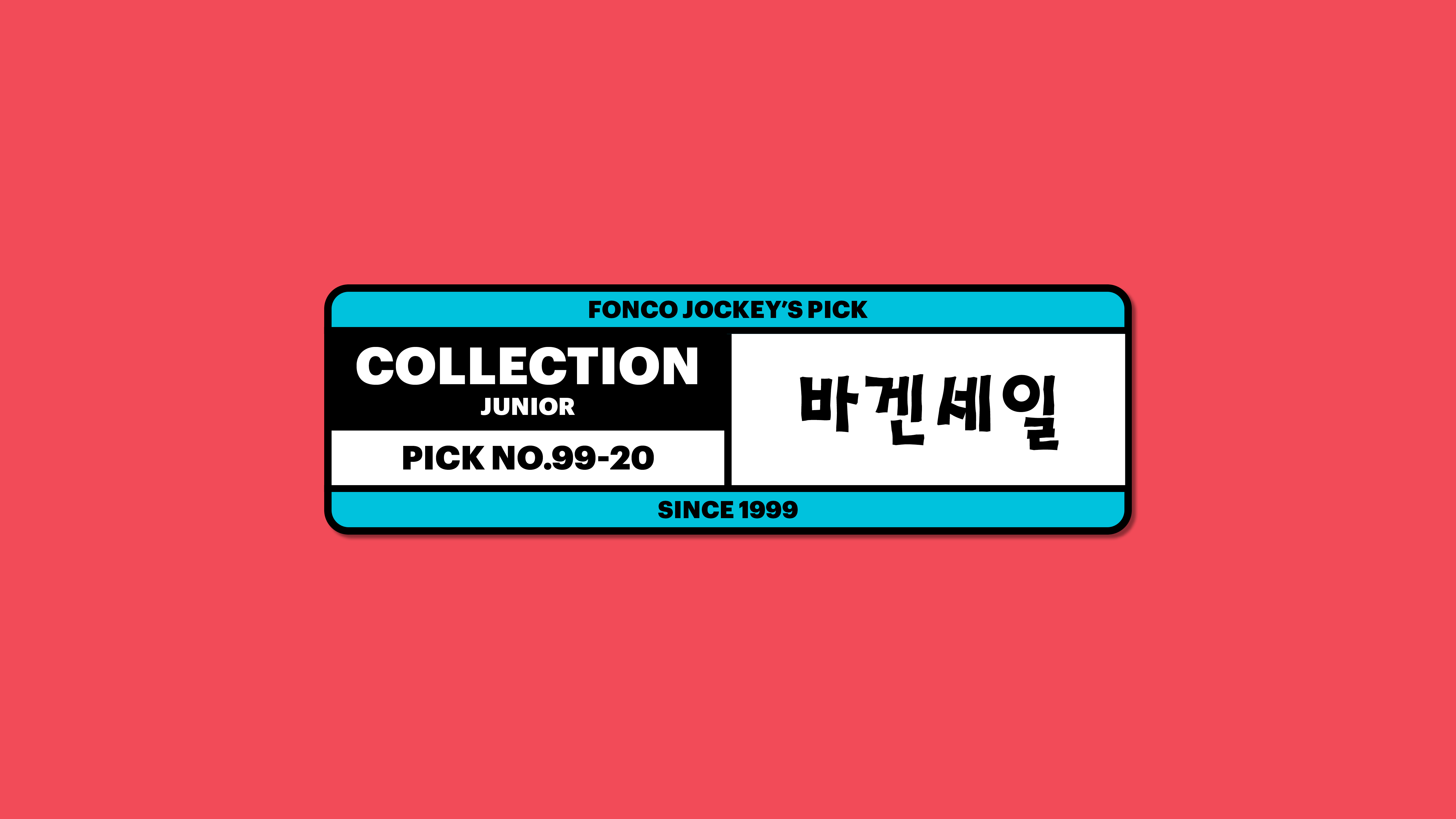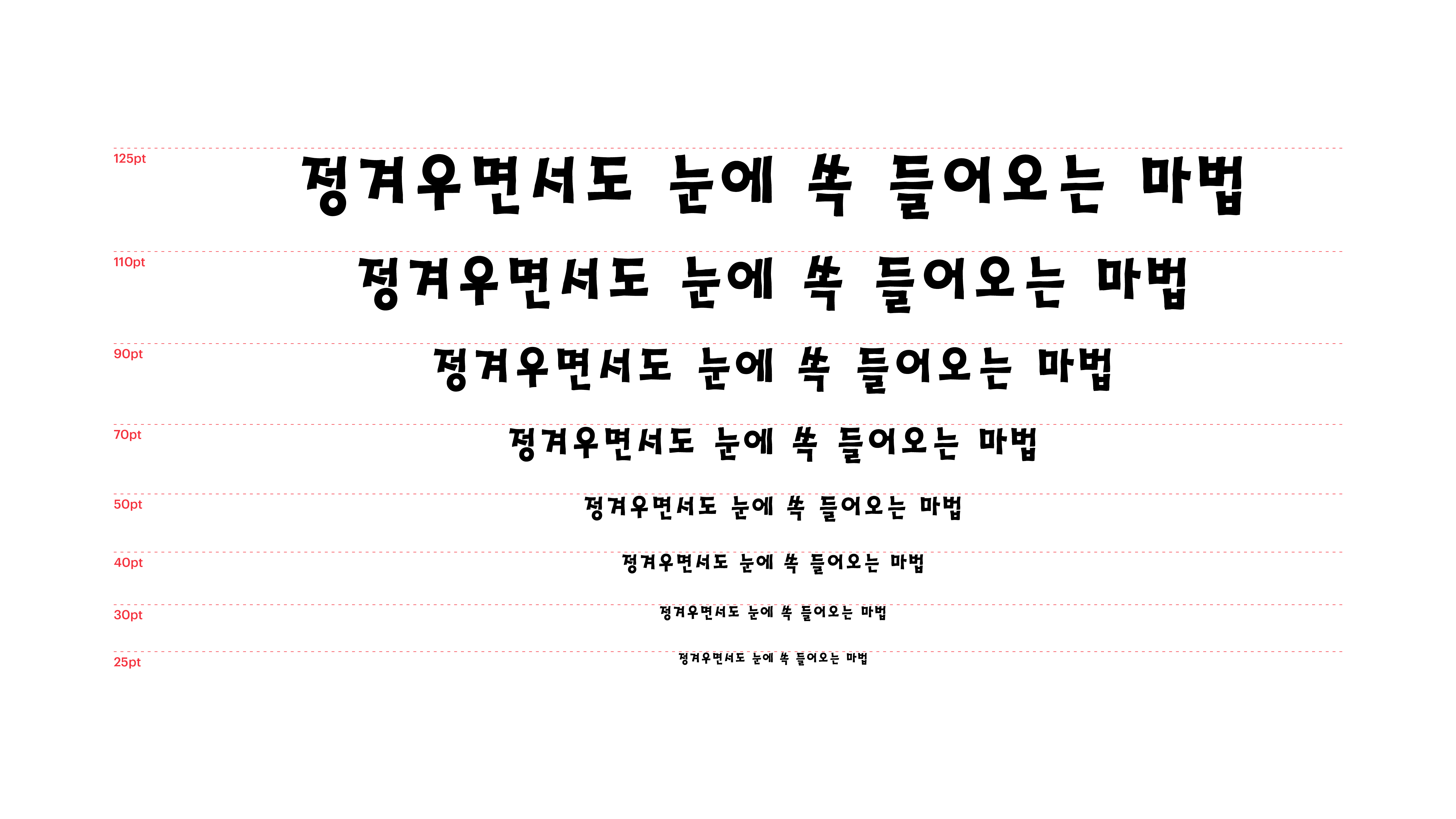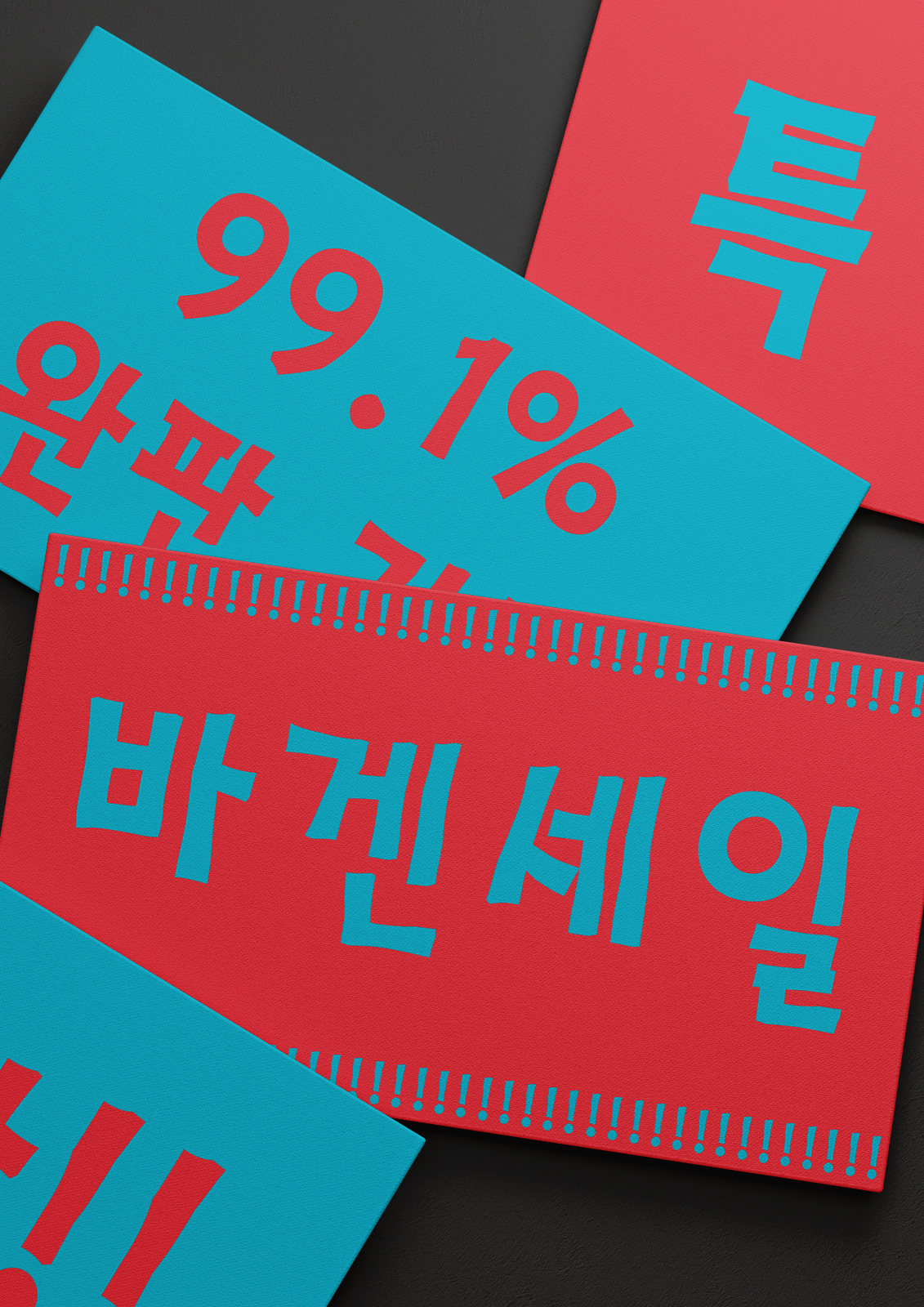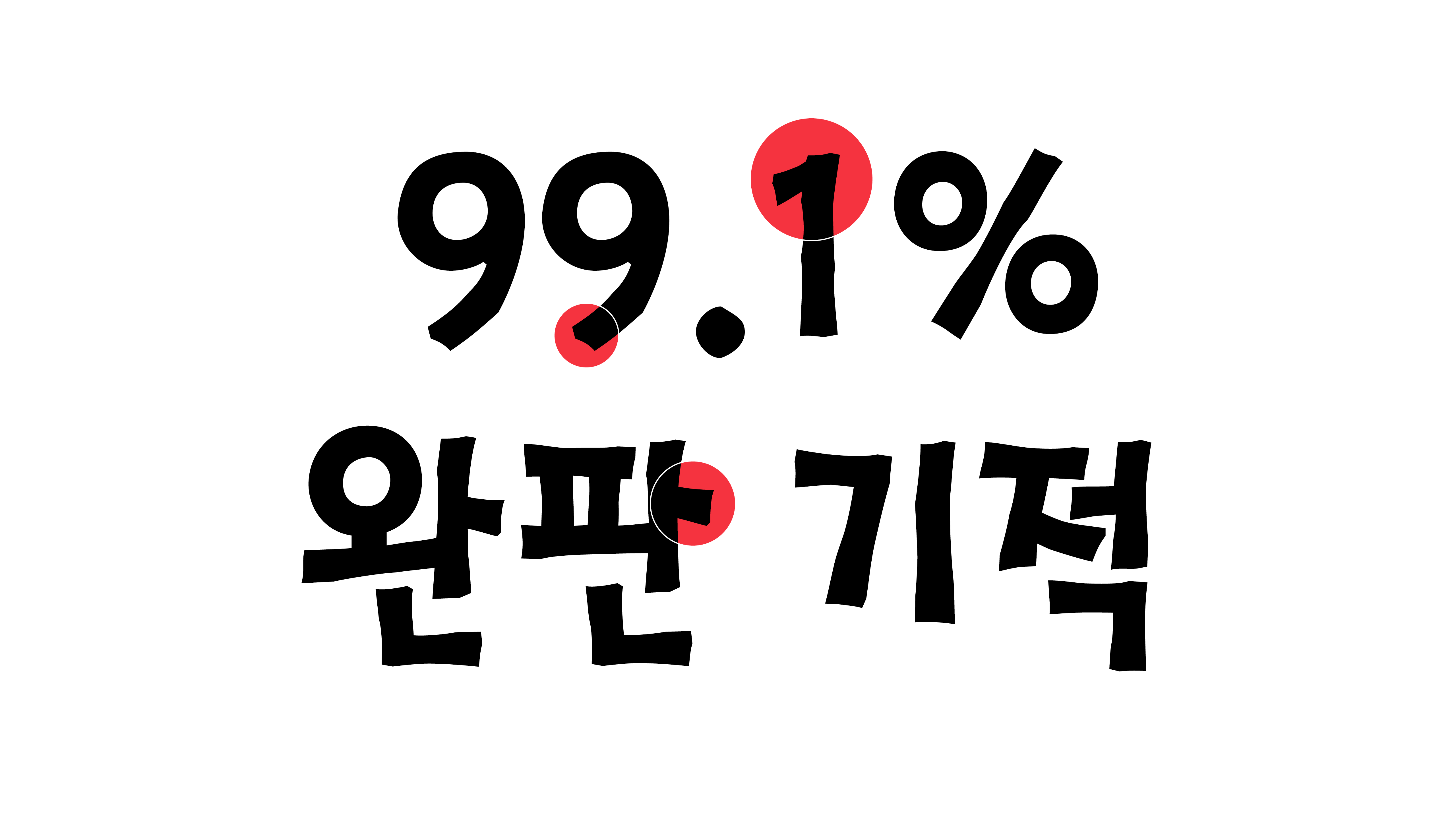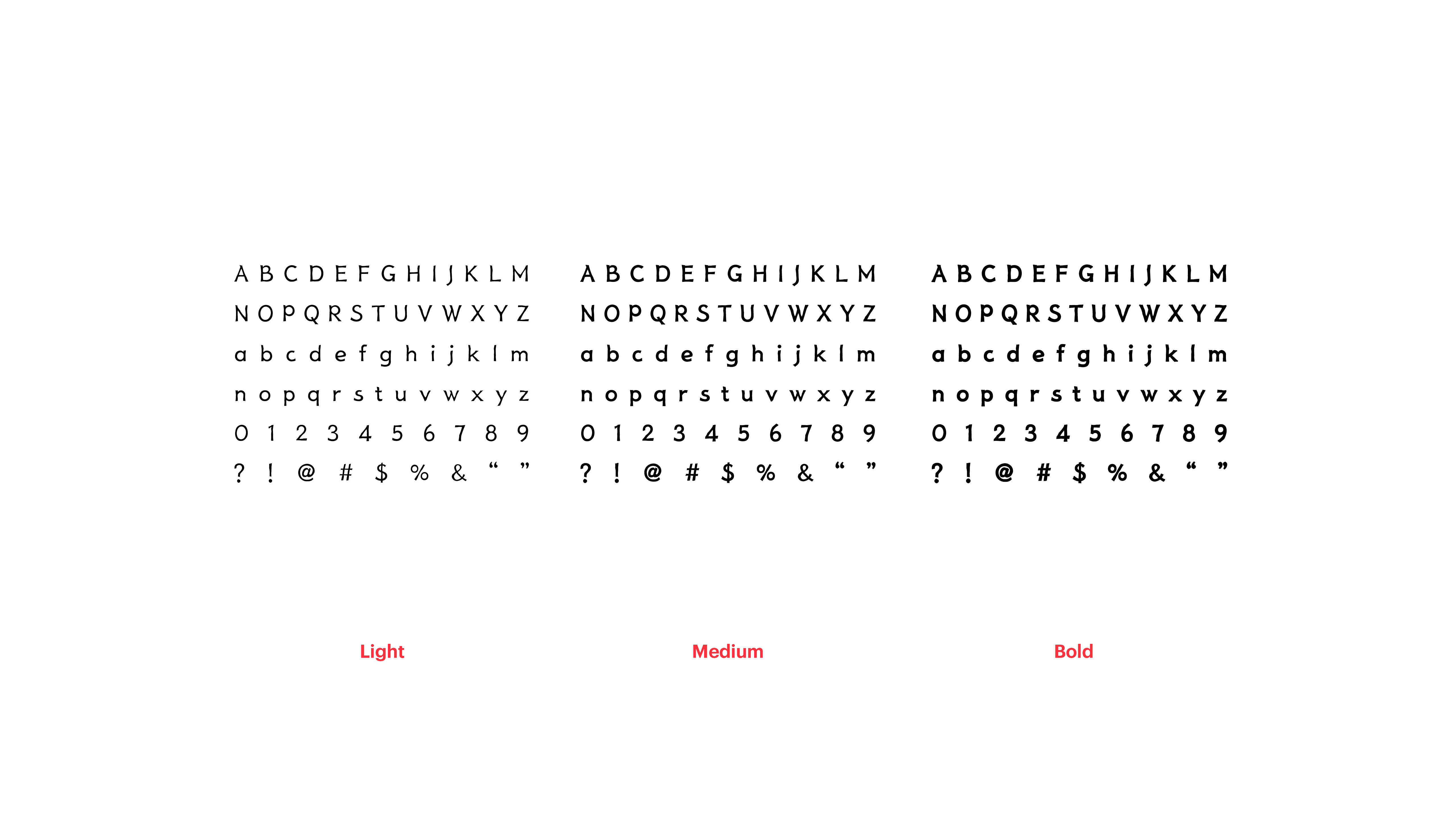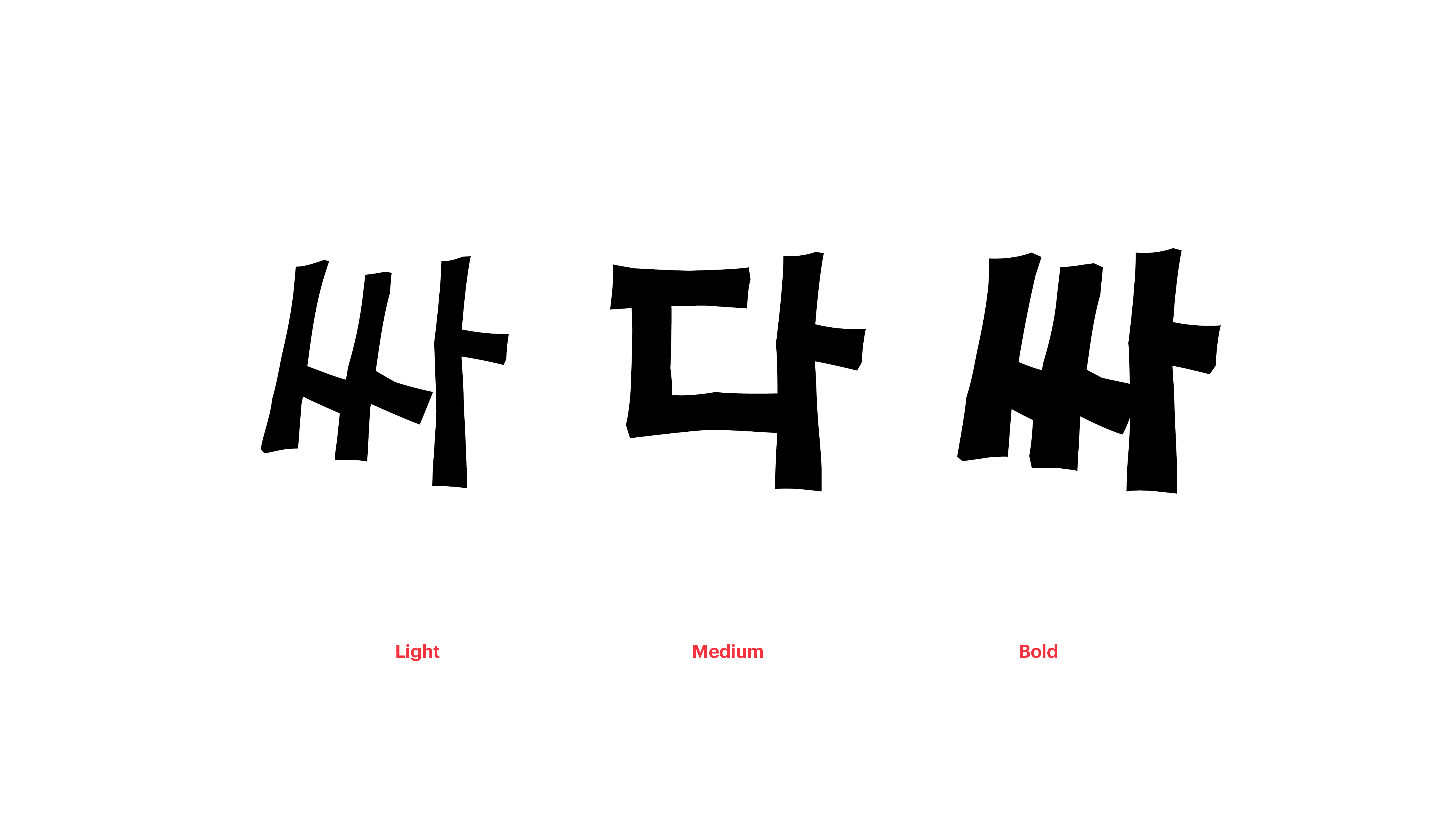
바겐세일
Yoon 바겐세일
내가 만든 물건들을 가지고 플리마켓에 나갈 때, 색다른 간판으로 고객의 이목을 사로잡고 싶다고요? 바겐세일체가 필요한 순간이네요. 납작한 붓이나 굵은 매직으로 직접 쓴 글씨처럼, 정겨우면서도 눈에 쏙 들어오는 마법의 폰트! 바겐세일체가 우리에게 완판의 기적을 안겨줄 거예요!